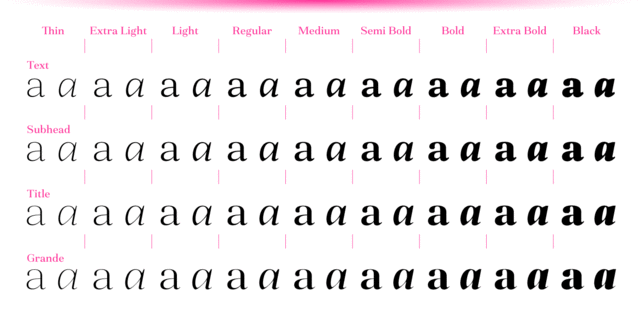
Версия шрифта для заголовков и названий. Fiorina – это антиква нового стиля, состоящая из 72 начертаний. Шрифт поставляется в 4 оптических размерах: от текстового с умеренным контрастом до суперконтрастного Grande. Каждый из 4 наборов имеет 9 весов с соответствующим изысканным курсивом. Общее разнообразие начертаний делает Fiorina идеальной гарнитурой для журналов. Набор глифов поддерживает все европейские языки на основе латиницы, а также все основные языки, в которых используется кириллица. Шрифтовое семейство также поддерживает многочисленные функции OpenType, включая 6 наборов цифр, капитель, дроби, надстрочные и подстрочные индексы, порядковые числа и многое другое. Шрифт разработал Андрей Константинов в студии Mint Type в 2020 году.
тонкий, легкий, деликатный, ровный, гармоничный, техничный, современный, статичный, культурный, образованный, устойчивый, твердый, четкий, резкий, острый, роскошный, гламурный, модный, ювелирный, художественный, богатый, дорогой, отборный, элитный, изысканный, худой, динамичный, серьезный, эффектный, качественный, городской, чистый, утонченный, прохладный, свежий, благородный, красивый, элегантный, мастерский, эстетичный, изящный, знаменитый, драгоценный, комильфо, романтичный, вежливый, строгий, стабильный, солидный, Строгий, убедительный, классический, интеллигентный, аристократичный, салонный, торжественный, звонкий, музыкальный, прекрасный, блестящий, глянцевый, гордый, серебрянный, серебристый, театральный, драматичный, творческий, сексуальный, выразительный, яркий, мотивирующий, авторитетный, внушительный, тяжелый, плотный, заметный, активный, броский